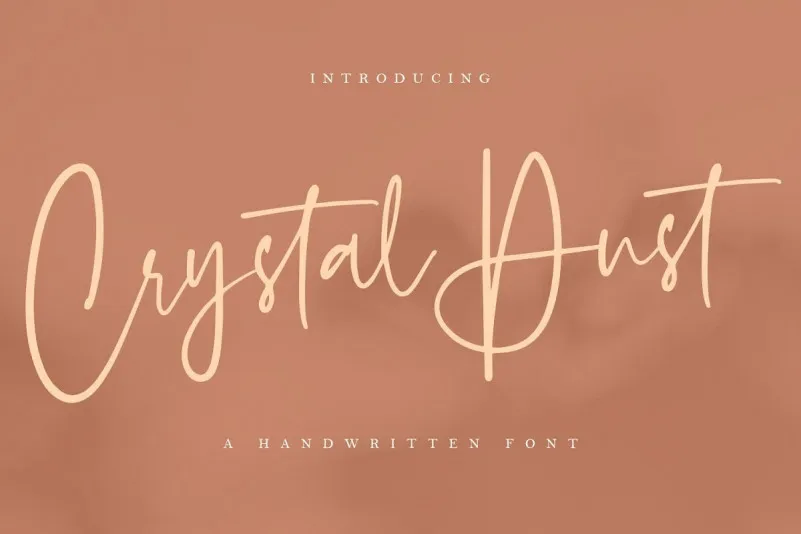
Crystal Dust Handwritten Font – Download Grátis
Crystal Dust é uma elegante fonte escrita à mão que traz uma sensação hipnotizante de delicadeza e sofisticação. Esta fonte foi projetada para capturar a essência do estilo moderno de escrita à mão, com seus traços suaves e simples, como se os letras flutudassem como danças sutis. Desenvolvida pelo designer zziplex, Crystal Dust oferece uma aparência perfeitamente natural e impecável, que é ideal para diversas aplicações gráficas. Esta fonte é especialmente adequada para projetos de estaçãoaria e convites sociais, onde seu estilo moderno e elegante pode criar um visual atraente. Além disso, ela também se destaca em logos, eventos como casamentos e criação de marca, bem como design gráfico geral, ajudando você a alcançar seus objetivos. Crystal Dust é uma escolha perfeita para qualquer projeto que deseje dar vida às suas ideias com um toque moderno e delicado de escrita à mão.